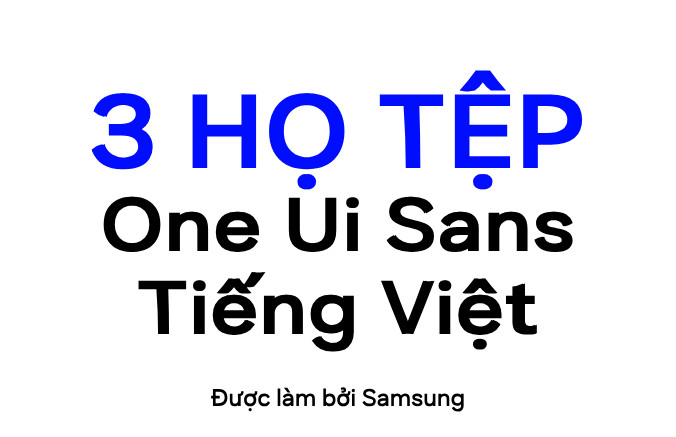
Phông tiếng Việt One Ui Sans (3 files)
Giới thiệu về Phông tiếng Việt One Ui Sans (3 files)
Trong thế giới thiết kế đồ họa hiện đại, việc tìm kiếm một bộ Font Miễn Phí chất lượng và hỗ trợ đầy đủ tiếng Việt là điều vô cùng quan trọng đối với học sinh và sinh viên. Bộ Phông tiếng Việt One Ui Sans (3 files) chính là giải pháp hoàn hảo mang phong cách tối giản nhưng vô cùng tinh tế của giao diện Samsung lên các thiết kế cá nhân. Với đường nét thanh thoát và độ tương phản cao, bộ phông này giúp nội dung văn bản trở nên dễ đọc và chuyên nghiệp hơn bao giờ hết.
Đặc điểm nổi bật của bộ phông
Bộ sưu tập này bao gồm 3 định dạng tệp tin cốt lõi, đảm bảo khả năng tương thích tuyệt vời trên nhiều nền tảng từ máy tính đến thiết bị di động. Điểm mạnh của Phông tiếng Việt One Ui Sans (3 files) nằm ở sự cân bằng giữa tính thẩm mỹ và công năng sử dụng. Các ký tự tiếng Việt được chăm chút kỹ lưỡng, không xảy ra hiện tượng lỗi dấu hay lệch dòng, giúp người dùng tự tin hơn khi trình bày tiểu luận hoặc làm slide báo cáo trên lớp.
Cách ứng dụng Phông tiếng Việt One Ui Sans (3 files) hiệu quả
Nhờ thiết kế sans-serif hiện đại, bộ phông này rất phù hợp cho các tiêu đề lớn cũng như các đoạn văn bản dài. Các bạn học sinh có thể sử dụng 3 tệp tin này để tạo ra sự phân cấp thông tin rõ ràng, giúp người xem dễ dàng nắm bắt nội dung chính. Ngoài ra, tính ứng dụng linh hoạt của nó còn mở rộng sang các dự án thiết kế web hoặc ứng dụng học tập trực tuyến, tạo nên một giao diện người dùng thân thiện và đồng nhất.